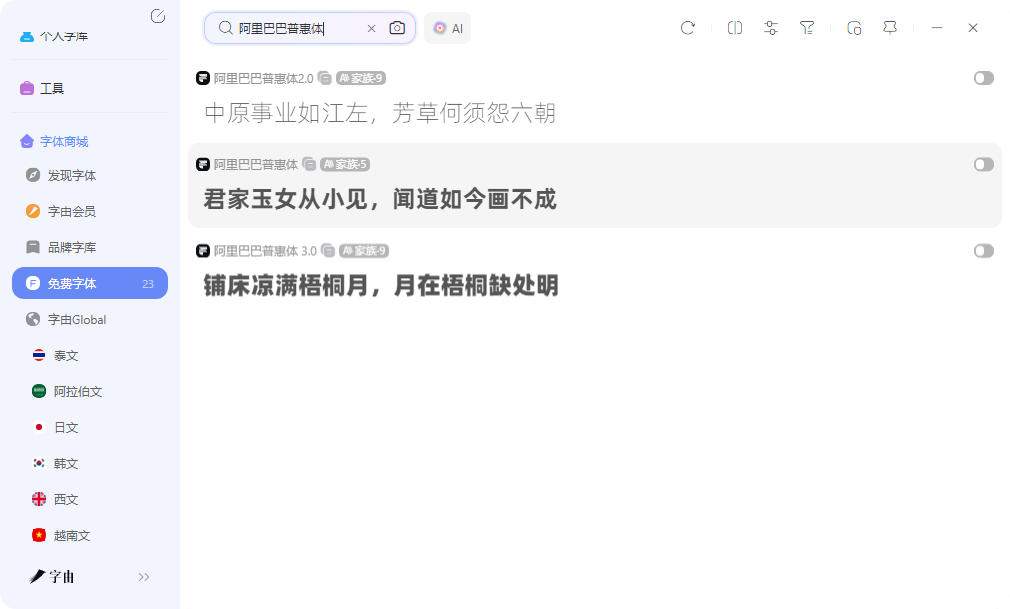
这些办公常用字体,设计师和企业都在用
制作一份PPT、撰写一份正式报告,或者设计一份内部刊物时,字体的选择直接影响阅读效率和整体质感。黑体适合标题,宋体适合正文,楷体适合引文,仿宋适合公文。这些基本规律大家都知道,但问题是:这些字体从哪里获取?哪些版本可以免费用于商业用途?换了电脑怎么快速装上?办公场景本身不需要太花哨的创意字体,最核心的需求是稳定、可读、授权清晰、跨设备可用。今天推荐5个获取办公常用字体的渠道,从一站式字体管理平台到正版字体库,肯定有你感兴趣的。
办公场景最常用的中文字体,按类别分就是黑体、宋体、楷体、仿宋。这四个类别基本覆盖了标题、正文、引文、公文的全部需求。字由的字体库在这几个类别上都做了专门收录,而且全部标注了免费商用状态。下面我会给大家做一些推荐:
黑体类:思源黑体(Adobe与Google联合开发的开源字体,7种字重,2025年字由搜索榜第一名)、阿里巴巴普惠体、优设标题黑、字由文艺黑等。
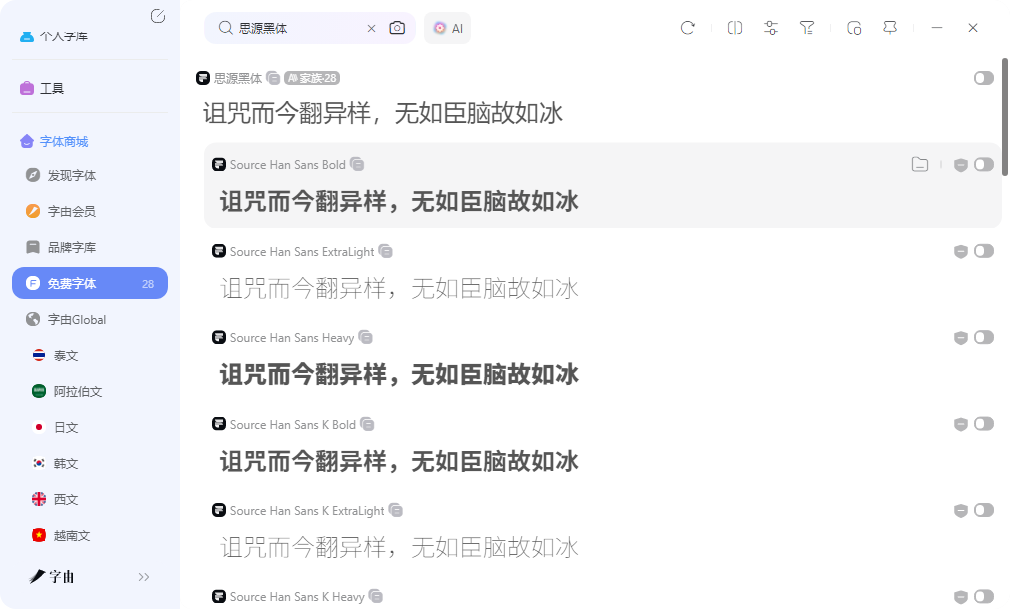
思源黑体适合网页和UI界面的正文排版,阿里巴巴普惠体适合电商和品牌营销场景。宋体类:思源宋体(思源黑体的姊妹篇,兼具传统宋体韵味与现代易读性,适合书籍和长文排版)、思印宋等。楷体类:阿里妈妈东方楷体、江西拙楷(古朴自然,适合传统文化类设计)等。仿宋类:方正仿宋等。办公设计中最头疼的英文配套字体的需求,字由的免费商用英文库也覆盖了Playfair Display(适合标题)、Oswald Medium(适合现代感设计)、Poppins Bold等,与中文字体搭配使用。